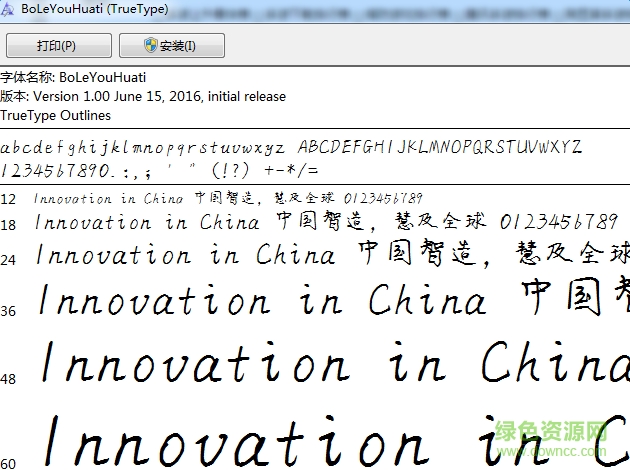
软件介绍 软件标签: 其他字体 字体 艺术油画体字体是一款超好用的中文个性字体,字体非常具有艺术气息,对于喜爱艺术的朋友来说这款字体绝对是你必不可少的收藏之一,喜欢的用户就赶快来绿色资源网免费下载收藏吧!艺术油画体字体安装方法方法一:控制面板/字体/文件/安装新字体;方法二:直接将字体复制到C:\WINDOWS\Fonts。方法三:针对win7系统,用户只需选中字体右键安装即可。注意事项本站所有字体资源仅供个人学习与参考,如需商业使用请到相关官网授权。小编测评艺术油画体字体是一款极具个性的字体,该字体十分飘逸,彰显了自己的个性,有喜欢的朋友可以来绿色资源网下载使用! 软件截图 上一张下一张(1 / 1) 安装详细截图 其他版本下载 标题 大小 更新日期 下载 下载地址 电脑版 艺术油画体 点击报错 软件无法下载或下载后无法使用,请点击报错,谢谢! 关闭报错反馈 请描述您所遇到的错误,我们将尽快予以修正,谢谢! *必填项,请输入内容 本类最新 dreamweaver字体库 首尔南山体字体 v1.06 官方版 潮字社风云简ttf 潮字社凌渡鲲鹏简体字体 潮字社曾玉波手书简字体 微博慧心字体 相关文章 Photoshop字体安装使用方法和技巧 如何解决“无法新增字体”问题 Win 7系统安装字体方法 网页字体大小设置方法 怎么改网页字体大小 在Linux系统中安装字体的几种方法 windows7字体显示问题:打开某些程序的时候显示的是乱码 用户评论 热门评论 最新评论 发表评论 查看所有评论(0) 昵称: 请不要评论无意义或脏话,我们所有评论会有人工审核. 字数: 0/500 (您的评论需要经过审核才能显示)